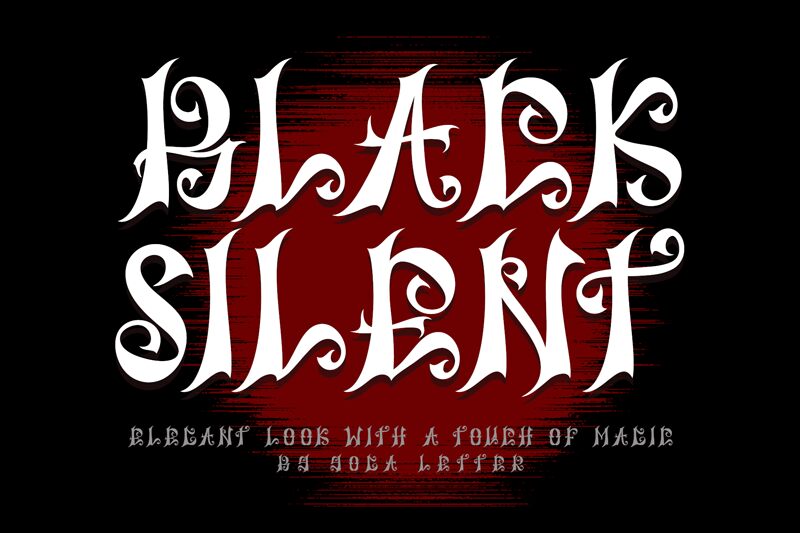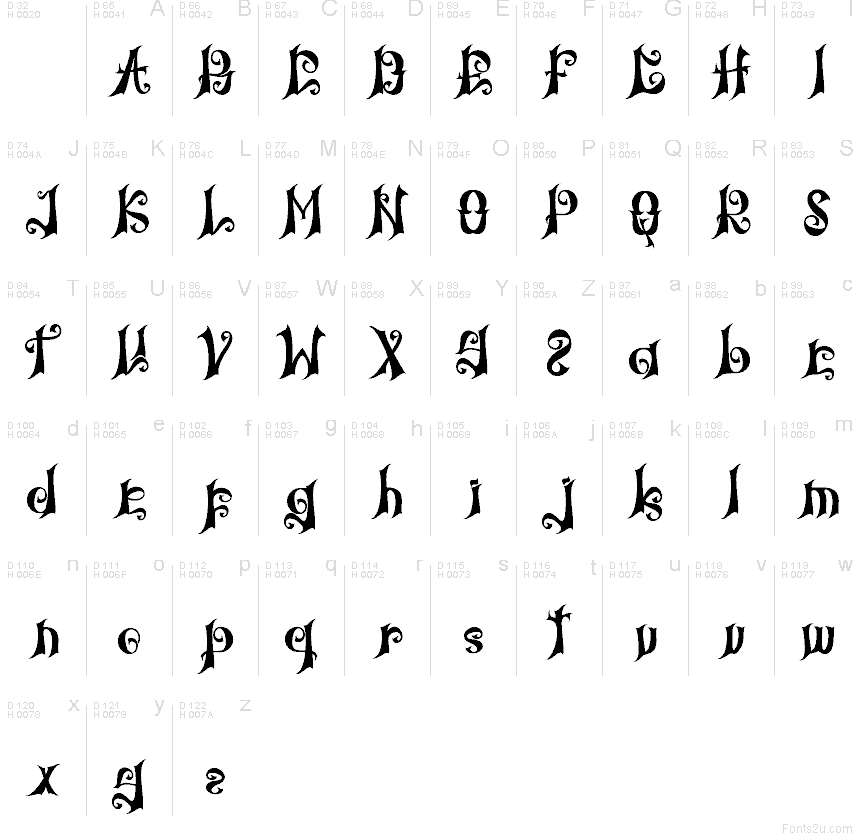
Black Silent
Black Silent de Yoga Letter es una tipografía gratuita para Halloween, caracterizada por sus formas altas y sinuosas, junto con trazos afilados que otorgan a las letras un aire oscuro, propio de un libro de cuentos. Gracias a sus bucles en espiral y cortes marcados, el conjunto parece más un grabado que un texto estándar.
Black Silent funciona de maravilla en carteles para fiestas de Halloween, folletos de casas encantadas, logotipos estacionales, letreros de tiendas de disfraces y etiquetas artesanales con un toque espeluznante. Esta fuente gratuita también es ideal para titulares decorativos, invitaciones a eventos y envases temáticos, siempre que busques un estilo que transmita la esencia festiva sin necesidad de ornamentos extra.